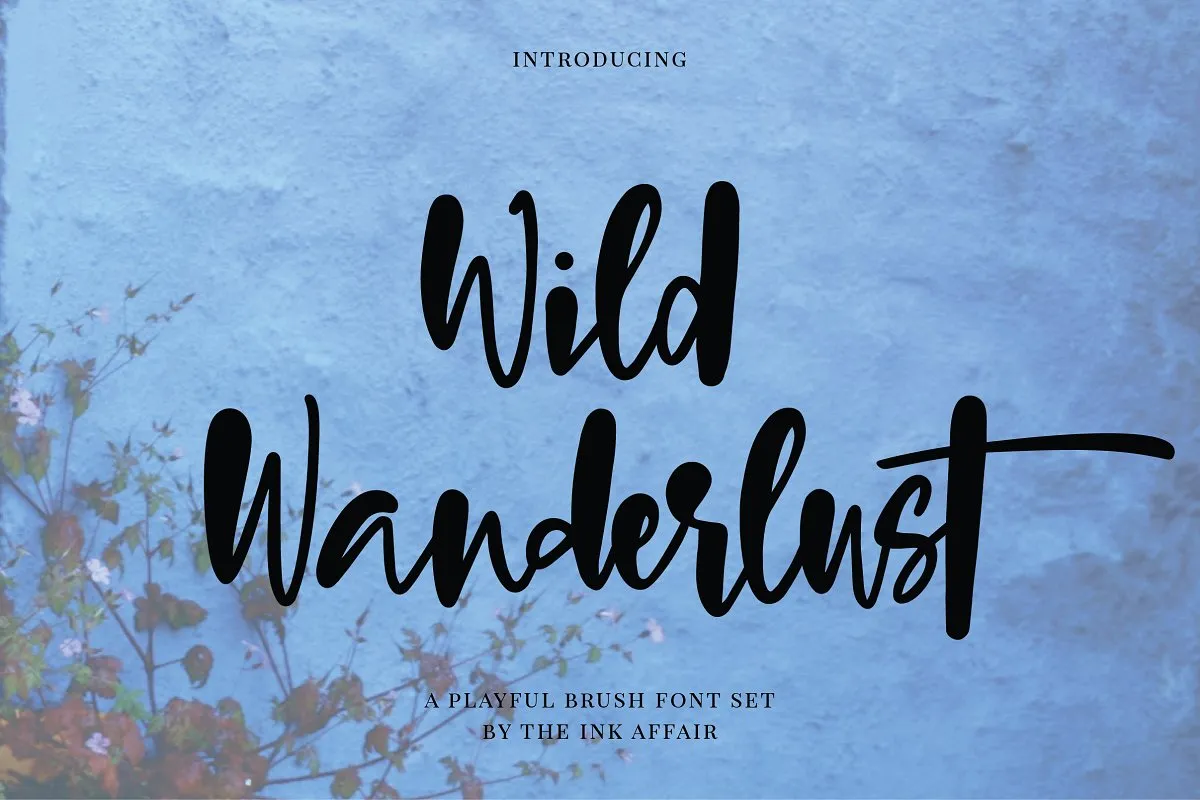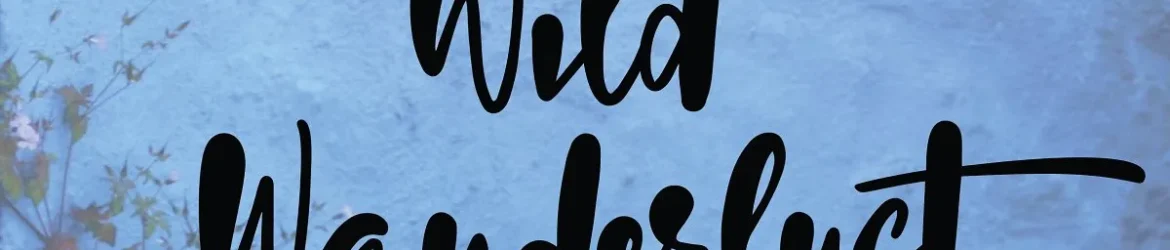
Wild Wanderlust Brush Font – Download Grátis
Introduzimos a Wild Wanderlust Font, uma fonte Brush que combina diversão e energia jogando com traços leves e espertos. Esta curiosa seleção de 2 conjuntos de letras maiúsculas e minúsculas é perfeita para aplicações criativas como casamentos, identidades empresariais e invitações românticas. Mas a Wild Wanderlust tem muitas outras aplicações além do papel. Seja para gráficos digitais, títulos, logotipos, convites de casamento, camisas, panfletos, sinalizadores ou até mesmo assinaturas de documentos – ela é um recurso imprescindível. A Wild Wanderlust é a fonte ideal para quem procura uma font que transmite vitalidade e emoção. Suas linhas contínuas e ricas texturas garantem que qualquer projeto seja imediatamente reconhecível e único. E não param por aqui: com o Wild Wanderlust, você tem um aliado perfeito para criar design gráfico que chama a atenção e se destaca no meio de uma multidão. Em suma, ele combina estilo, versatilidade e personalidade em uma fonte que realmente faz seu público falar de si mesmo.